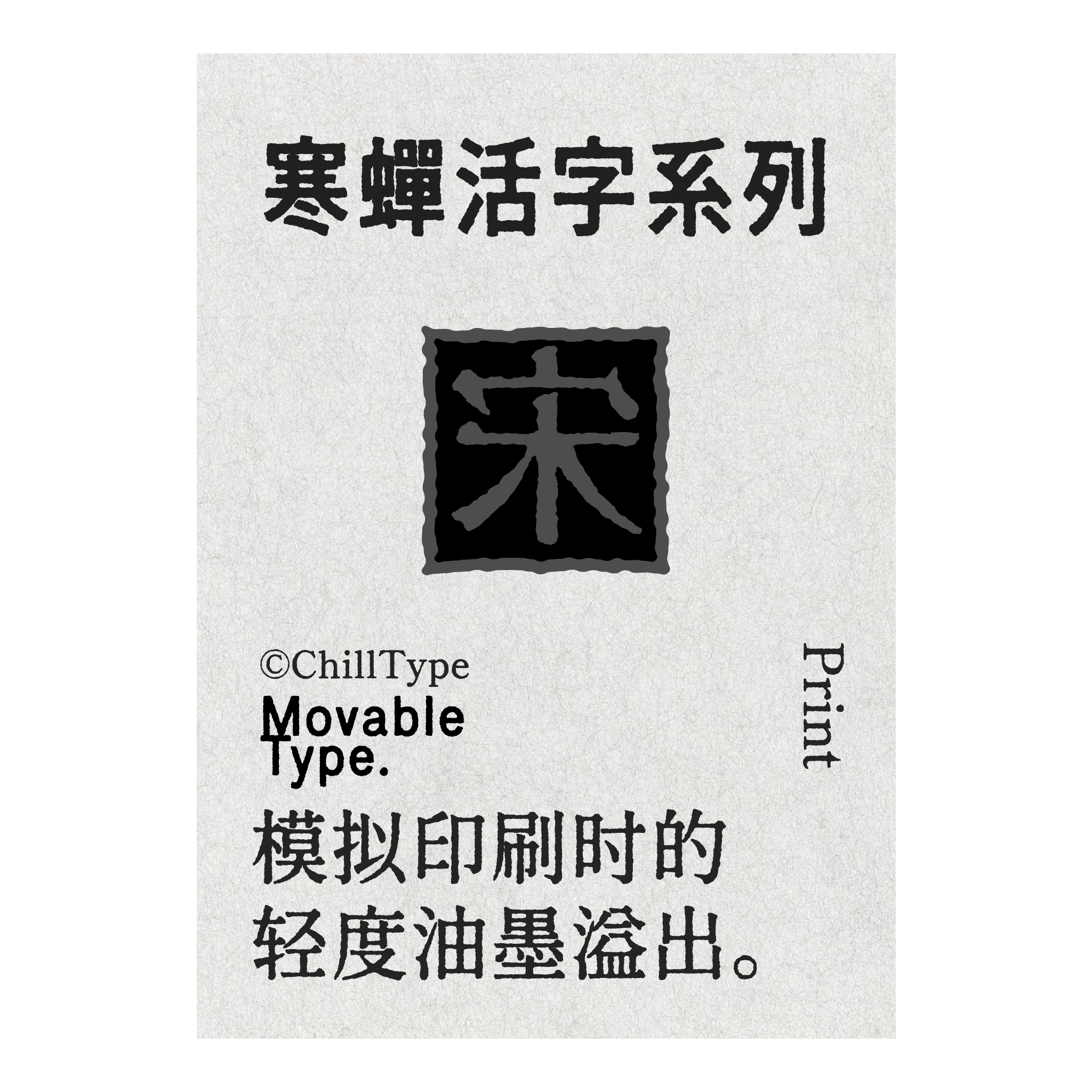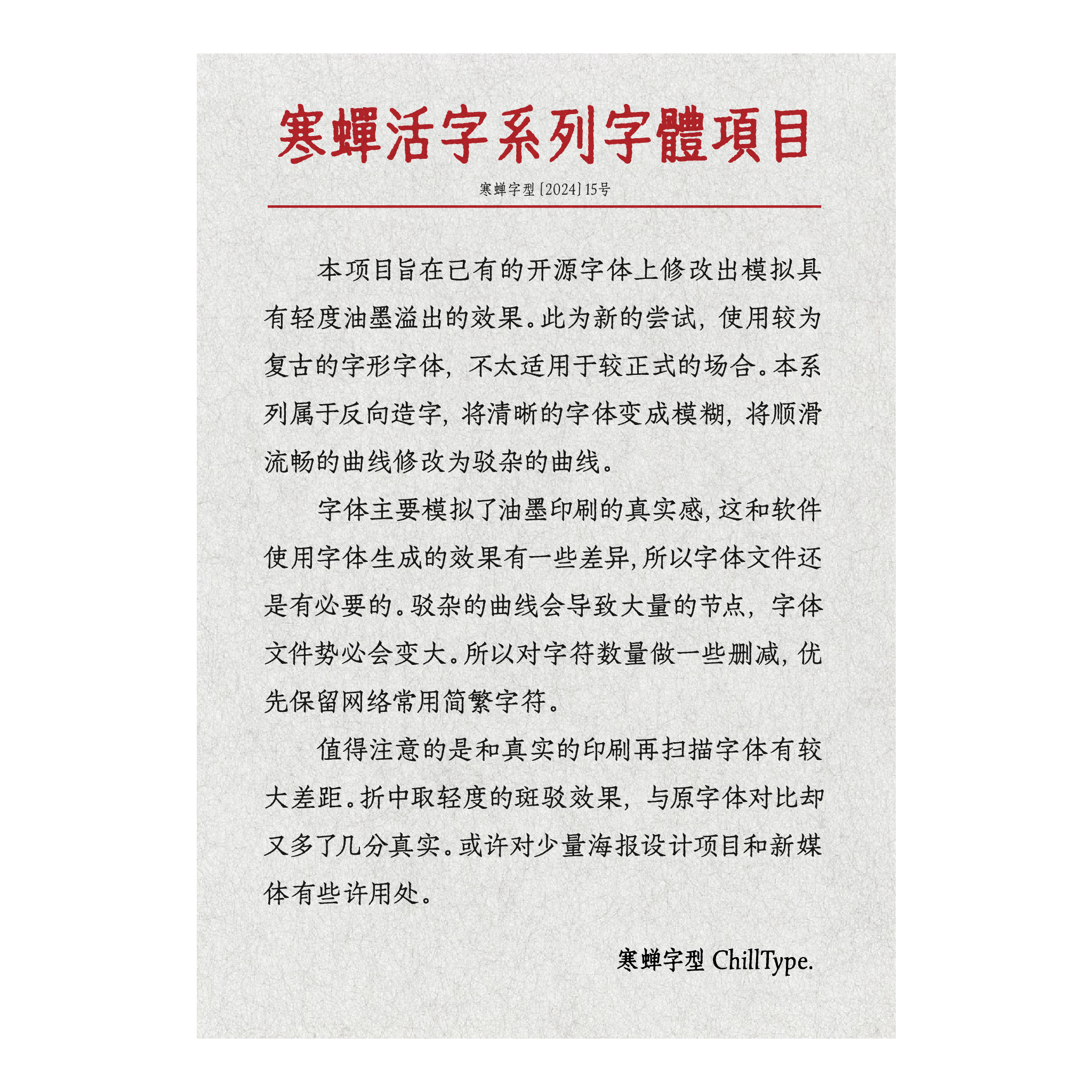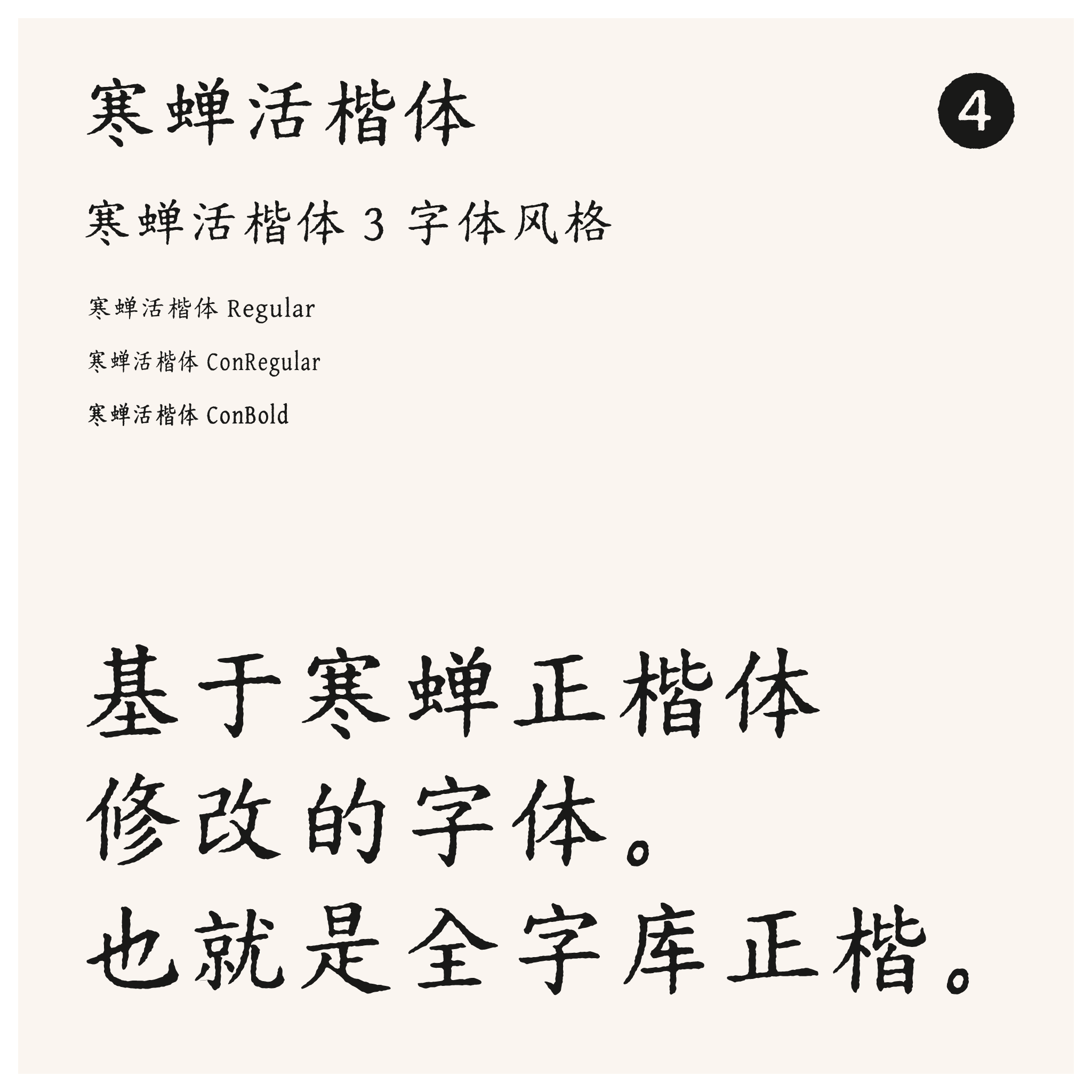
寒蝉活楷体是一款充满复古韵味的字体,其字形设计承袭了经典正楷的骨架与笔画,同时融入了独特的斑驳纹理,营造出一种历经岁月沉淀的沧桑感与手作质感。这款字体是在广受认可的寒蝉正楷体基础上进行修改与再创作而来的,可以看作是寒蝉正楷体的一个风格化变体。它属于更广泛的全字库正楷体系的一部分,该体系致力于提供一套完整、规范且具有美感的中文字符集。在保留原版寒蝉正楷清晰易读、结构严谨的特质之外,寒蝉活楷体通过精心添加的磨损与颗粒效果,使得每个字都仿佛从古籍碑帖中拓印而来,增添了浓厚的文化底蕴与艺术气息,非常适合用于追求古典、文艺或复古视觉风格的设计场景。
寒蝉活字系列,展示模拟印刷时轻度油墨溢出的活字“宋”。
寒蝉活字系列字体项目文档
寒蝉活黑体、寒蝉活宋体、寒蝉活仿宋、寒蝉活楷体、寒蝉活仿楷。
展示同一诗句“野田春水碧于镜”的不同中文字体呈现,包括寒蝉活黑体/宋体、思源黑体(模拟斑驳纹理)、源云明朝(朦胧效果)、汇文明朝(真实印刷扫描)的样式对比。
寒蝉活楷体介绍:含 Regular、ConBold 三种字体风格,为基于寒蝉正楷体(全字库正楷)修改而成的字体。
字体样本展示图,包含'草窗韵语'、'时光照相馆'、'有機食品 綠色環保'、'新年快樂'、'中國製造'和'活字印刷體'等多种字体示例。